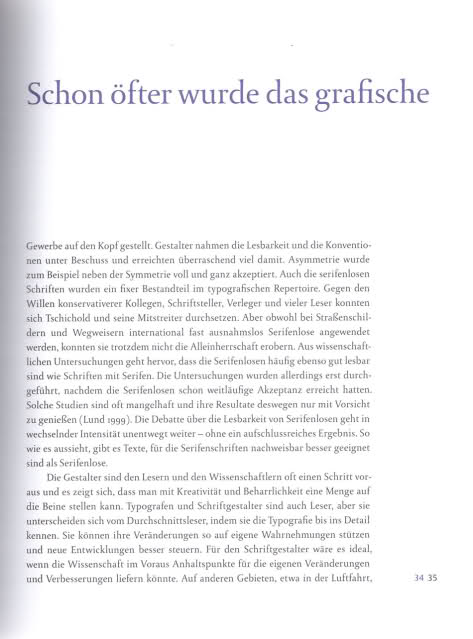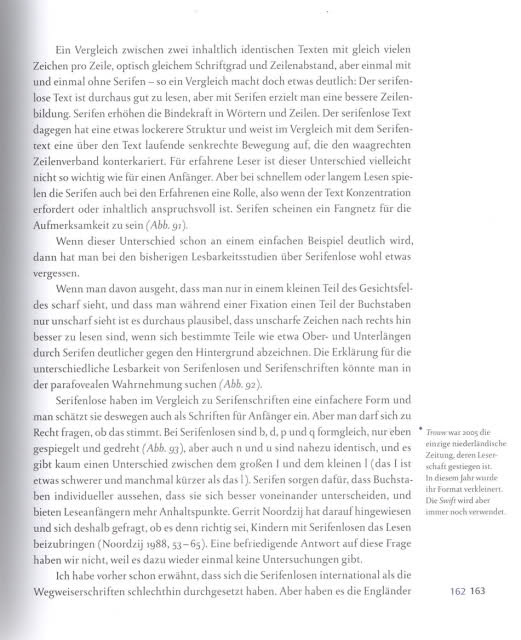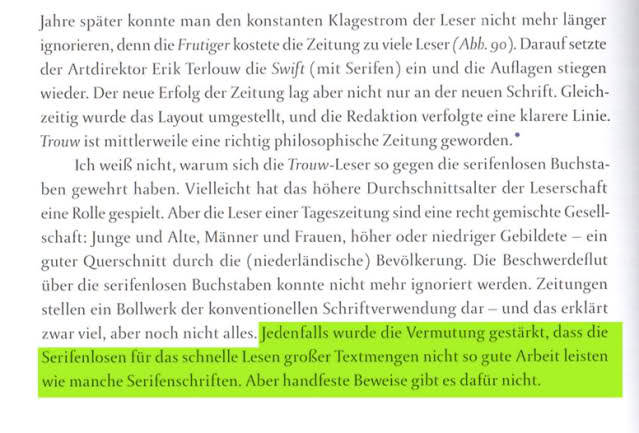
Lesbarkeitstests
Vergleichen die Pharmafirmen überhaupt Serifen- und Steinschriften miteinander? Hast Du irgendwo eine Beschreibung dieser Tests gefunden?
Beipackzettel sind im übrigen auch wieder ein besonderer Fall: Die Schrift ist meistens ziemlich klein. Die meisten digitalen Antiquas sind für eine Schriftgröße von etwa 12 Punkt gestaltet. Verkleinert man die auf die Größe, die in Beipackzetteln üblich ist, sind sie natürlich schlecht lesbar. Steinschriften vertragen eine solche Verkleinerung etwas besser, da sie keine dünnen Linien haben.
Um ein wirklich aussagekräftiges Ergebnis zu bekommen, müßte man mehrere verschiedene Schriften, die für die tatsächlich benützte Größe geschaffen wurden, miteinander vergleichen.
Lesbarkeitstests sollten die Verständlichkeit berücksichtigen, um vergleichbare Ergebnisse zu liefern.
Dafür interessieren sich Leute wie wir und Zeitungen. Die Typografie bei einer Zeitung ist auf Aufnahme und korrekte Verarbeitung hin optimiert. Da die Serifen den Blick wie auf Schienen führen, ist weniger Konzentration nötig. Man liest entspannter.
Das funktioniert leider nicht auf den Bildschirmen, da das Pixel viel gröber ist als das Druckraster und sich Serifenschriften daher nur in größerer Schriftgröße entspannt lesen lassen.
Ein paar weitere unbelegte Mutmassungen:
Ob eine Schrift gut lesbar ist, ist eine Frage der Gewöhnung. Zu Beginn des 20. Jahrhunderts hätten Frakturschriften demzufolge in deutschen Lesbarkeitstest besser abgeschnitten als heute, weil sich die Leute an diese Formen und ans ? gewohnt waren. Heute werden immer mehr Texte serifenlos geschrieben, und deshalb werden diese Schriften nun auch als besser lesbar empfunden.
Serifen bilden eine Linie, die es vereinfacht, der Zeile zu folgen und sie von den anderen abzugrenzen. In mehrzeiligen Texten sollte es weniger vorkommen, dass man auf der falschen Zeile weiterliest. Oder anders ausgedrückt: Serifenlose Texte brauchen einen grösseren Zeilenabstand.
Bei schlechter Auflösung (gegeben durch Bildschirm, Drucker oder Augen bei weit entfernten Schildern oder kleinen Schriften) ist die Unterscheidbarkeit der Buchstaben kritisch. Dabei können klare Öffnungen, wie sie etwa die Verdana oder die Frutiger haben, helfen.
Aufgrund des geschilderten Tests gäbe es keine signifikanten Unterschiede egal welche Webschrift man nimmt.
Persönlich lese ab einer gewissen Größe luftige Serifentexte wesentlich lieber. Einfach schöne Typografie. Auch wenn es nicht zur Lesbarkeit beiträgt, macht es einfach mehr Spaß und die Quelle wirkt seriöser, professioneller.
Auf der anderen Seite kenne ich jemand, der ClearType nicht mag und die Pixel genau sehen möchte. Das ist für ihn scharf und knackig, alles andere verschwommen und undeutlich.
Ich habe durch jahrelange Beschäftigung mit dem Thema "Lesbarkeit" folgendes herausgefunden:
Ja, Serifenschriften kann bei langen Texten eher besser lesen.
Ja, die Lesbarkeit hängt allerdings auch von der Zurichtung, Spationierung, dem Verhältnis Schriftgröße zu Zeilenabstand und andere Faktoren ab.
(Es gelingt mir leicht, beim gezielten verändern vorher genannter Faktoren auch eine Serifenschrift ganz schlecht lesbar zu machen.)
und:
Nein, das alles gilt nicht für ultrakurze Texte wie sie in der Werbung oft benötigt werden.
(da kann z. B. eine Serifenschrift auf einem bunten Bild völlig "absaufen" und somit unleserlich werden und eine ausgefranste, an sich schlecht lesbare Schrift, plötzlich perfekt funktionieren)
Musterbeispiel guter Lesbarkeit und Typographie: das Magazin "band eins" - da stimmt alles.
Das beste, was ich dazu kenne ist eine Zusammenfassung und Zusammenschau älterer und jüngerer Untersuchungen.
Die Ergebnisse:
• 1. Ein Vergleich zwischen Stilarten Serif/Sans Serif ist Unsinn, weil es in beiden Gruppen gute und schlechte und alles was dazwischen ist gibt.
2. Seriflose Schriften unterscheiden sich in der Lesbarkeit z.B. auch
untereinander, v.a. weil es ja Rennaissance-Antiquas vs. Klassizistische vs. Egyptienne und Antiqua-Varianten gibt.
3. Der Vergleich zwischen zwei Schriften Serif/Sans Serif zeigt umso mehr Vorteile in der Lesbarkeit, je älter die Untersuchung ist. D.h. früher – als die Menschen nur Serif gewohnt waren und die seriflosen als »grotesk« empfunden wurden – waren die Serifschriften besser lesbar.
4. Unter Einbeziehung aller Satzvariablen ergab sich ein Vorteil für ansonsten gleich gut lesbare Sans Serif-/Serif-Schriften, wenn der Zeilenabstand immer weiter reduziert wurde (Was man aber ohnehin nicht tun sollte.). Wenn man also in einem längeren Werk bei gleich guter Lesbarkeit einen Druckbogen sparen will, indem man zwei Zeilen mehr pro Seite unterbringt, empfiehlt sich eine gut lesbare Rennaissance-Antiqua (sehr häufig eine Garamond). Bei den Textmengen in der Werbung fällt dieser Faktor nicht ins Gewicht.
die Diskussion serifen oder keine beenden. Zur ersten Aussage:
ich weiß das Leute die zwischen 18-25 sind
häufig eine serifenlose Schrift für "normal" halten
und serifen Schriften eher ein zusätzlicher Charakter zuschreiben;
soll heißen, sollten wir mehr serifenlose Schriften benutzen, wird
vielleicht aus der "Serif" bald die "Fraktur" (das natürlich nicht so stark :)
soll heißen, sollten wir mehr serifenlose Schriften benutzen, wird
vielleicht aus der "Serif" bald die "Fraktur" (das natürlich nicht so stark :)
Gerne und dann stark ;-).